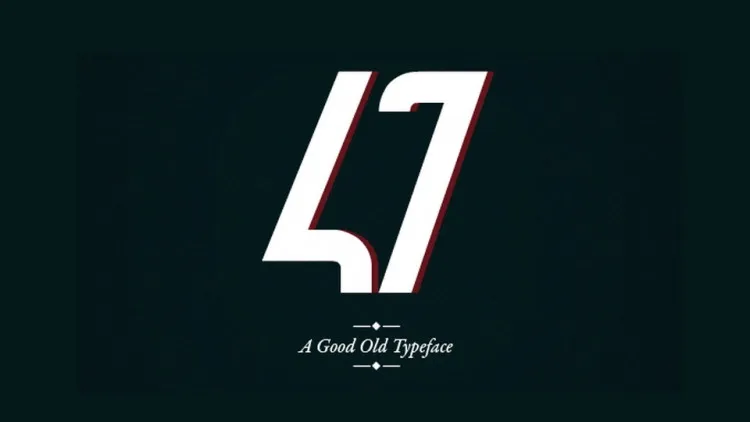
47 Typeface – Download Grátis
Esta é uma fonte sans-serif que tem tudo para conquistar seu design gráfico. 47 Typeface foi criada pensando em incorporar os traços mais modernos e contemporâneos, enquanto mantém um toque nostálgico na medida certa. Inspirada nos posters de cinema, nas placas das ruas ou nas fotografias que remetem ao passado, essa fonte tem o poder de ressuscitar memórias através do design visual. A sua característica mais notável é a forte presença em qualquer ambiente, tornando-a perfeita para aplicação em posters e colagens. A minimalista elegância da 47 Typeface permite que seja utilizada em uma vasta gama de cenários, adaptando-se facilmente aos mais diversos estilos. Como fonte sans-serif, ela é perfeitamente capaz de se destacar sozinha ou combinar com outros tipos para criar designs atemporais e atraentes. A Hamilton está aqui para inspirá-lo no desafio constante de inovar e explorar novas ideias através do design visual. Experimente essa fonte, você não irá se arrepender.